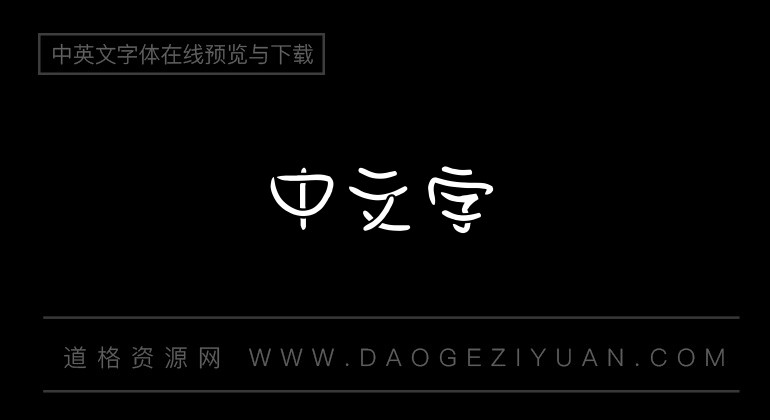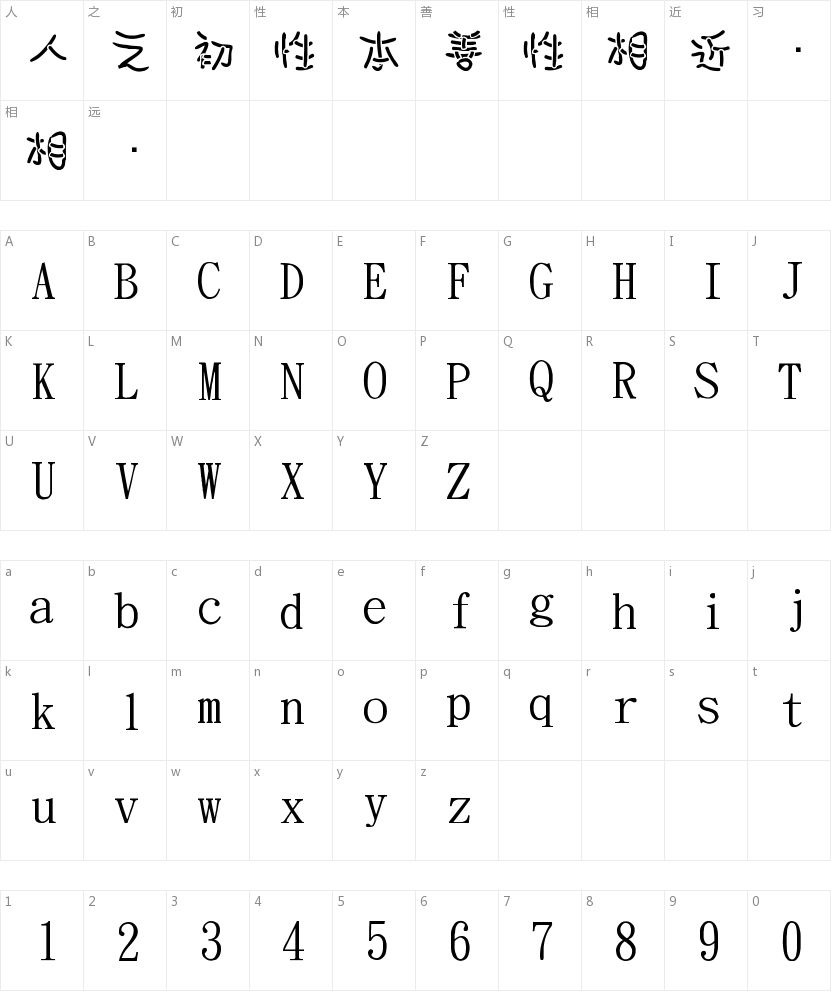
金梅浪漫小胖字体
金梅浪漫小胖字体是一款由金梅设计的新颖可爱的字体,拥有温暖的粗细线条,让人看起来更加温馨浪漫,可以用于各种类型的文字排版,比如广告、网站、报纸、杂志等。它的特点是有一种温暖的质感,可以营造出一种安静、温暖的氛围,使用者可以根据自己的需求进行调整,让文字显得更加浪漫可爱。
金梅浪漫小胖字体是一款非常不错的手写艺术字体,具有很好的视觉感,适合于文化类的宣传设计、商业类品牌的广告和产品包装设计以及个性化文字排版等较多场景。
金梅浪漫小胖字体字符映射图